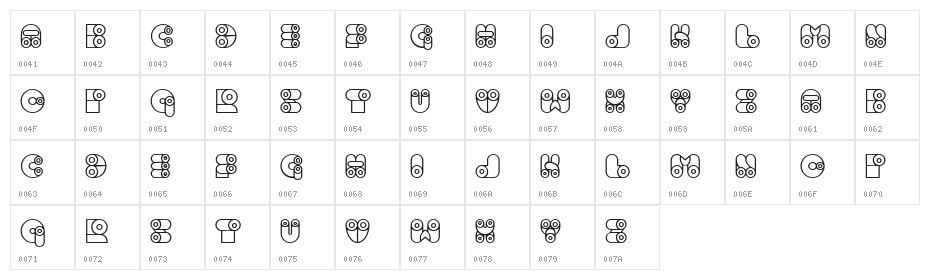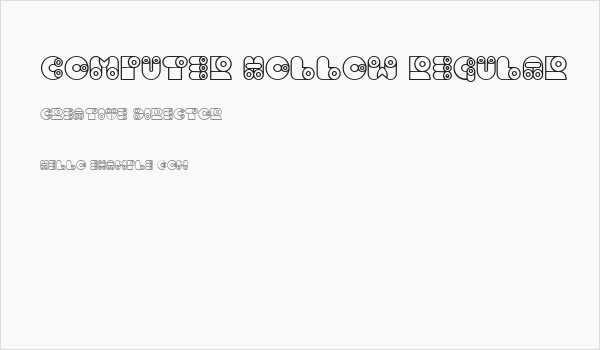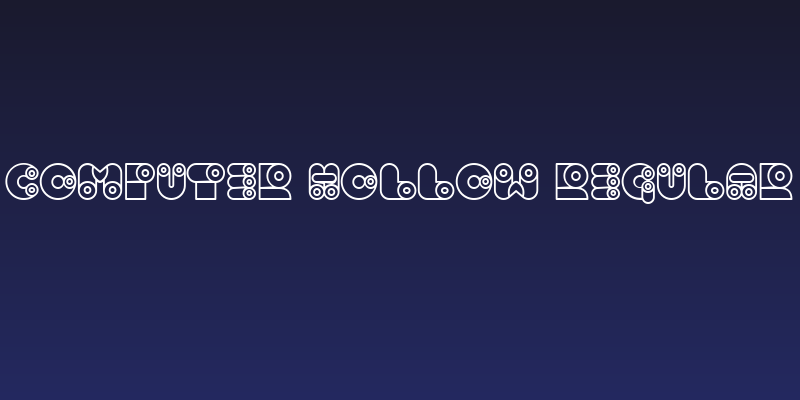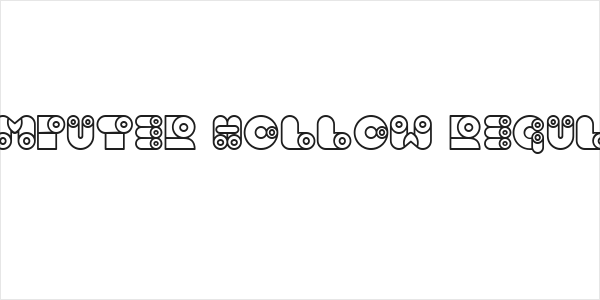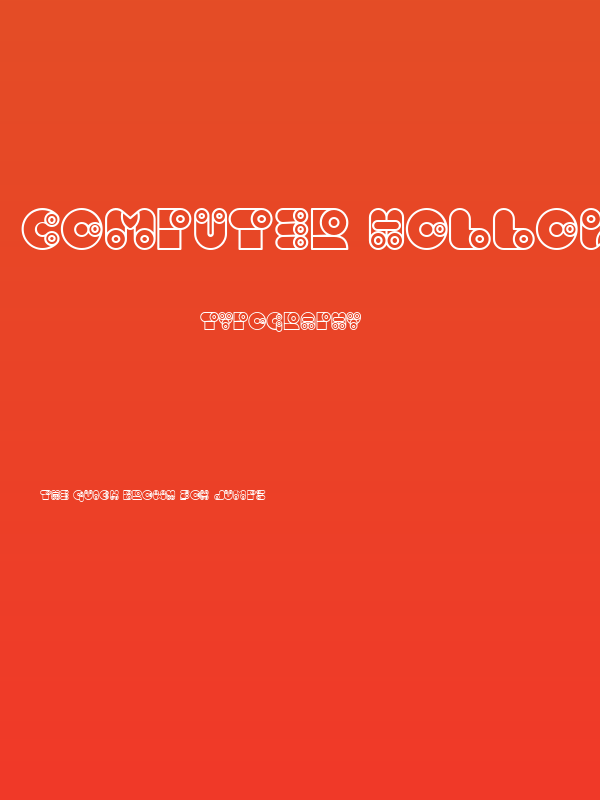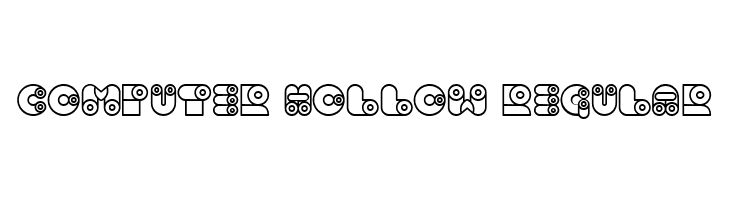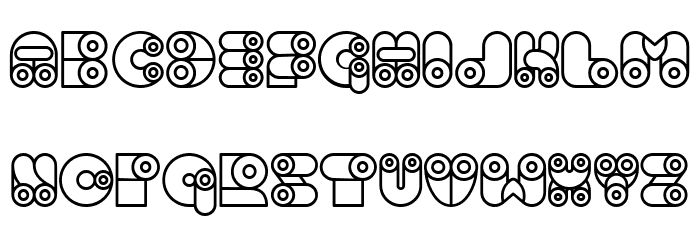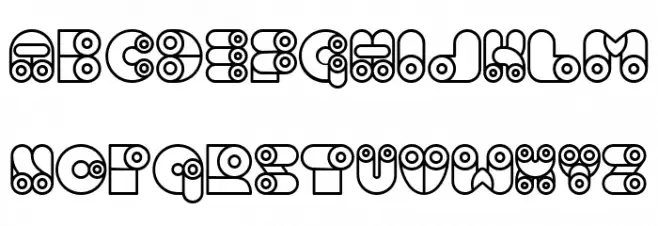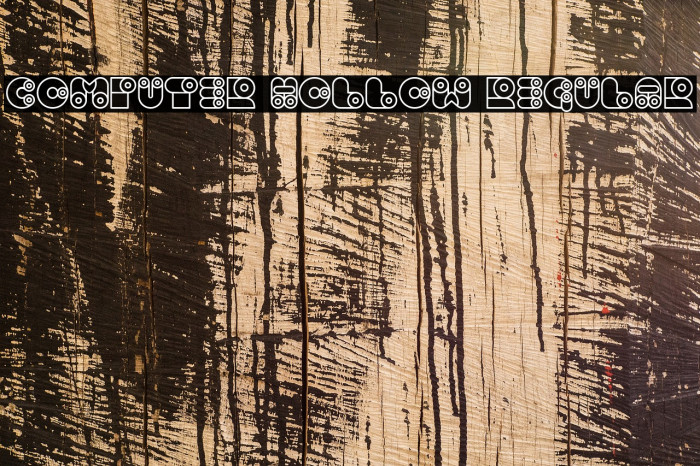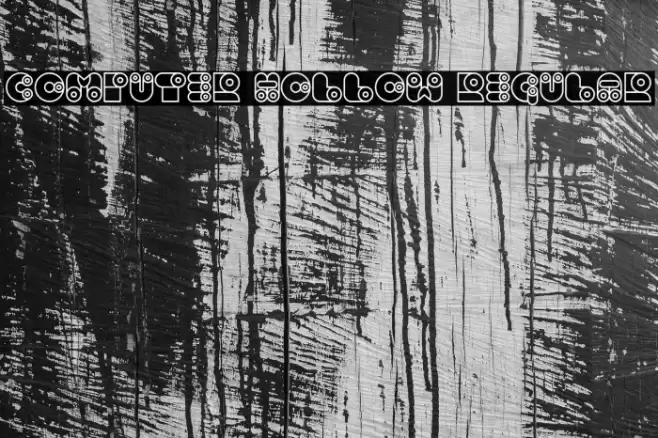
Computer Hollow Regular Font
| Progetti proposti | Ideal for posters, album covers, digital art, and branding that requires a modern and artistic flair. |